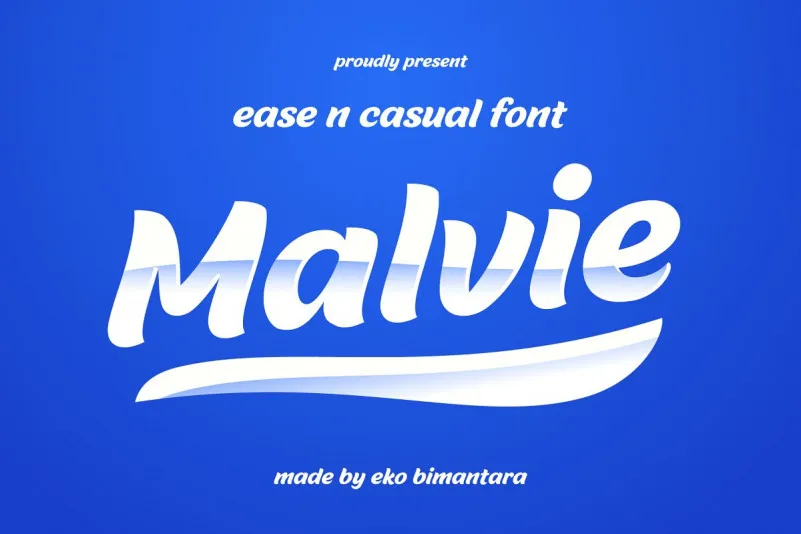
Malvie Bold Script Font – Download Grátis
Olá! Estou aqui uma fonte alegre e casual chamada Malvie Bold Script para vocês. Recentemente lançamos uma nova fonte bold script que incorpora influências do estilo tipográfico de letras entrelaçadas, logotipos de texto grosso e fuentes kids. Malvie é um projeto criado por Eko Bimantara, inspirado nas lembranças delicadas da mão que escrever letras. Esta fonte casual e descontraída é ideal para o título de seus projetos, embalagens e rótulos de produtos, marcas de empresa e outros materiais que exigem um estilo brilhante e audacioso. A característica mais atraente desta nova adição à nossa gama de fonts é seu design dinâmico, com suas curvas marcadas especialmente em suas partes finas. A M0Type compartilha esta fonte para que vocês possam usá-la em diversas aplicações gráficas e corporativas. Seja o próximo produto ou a próxima campanha publicitária, Malvie é uma excelente escolha para dar um toque de personalidade e alegria ao seu design.